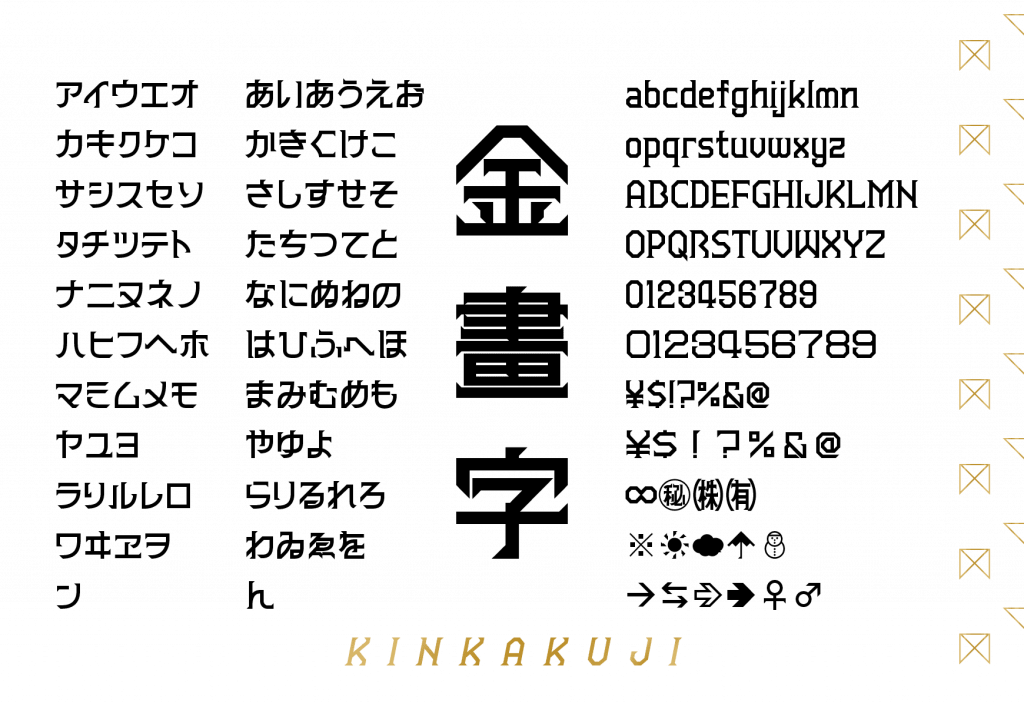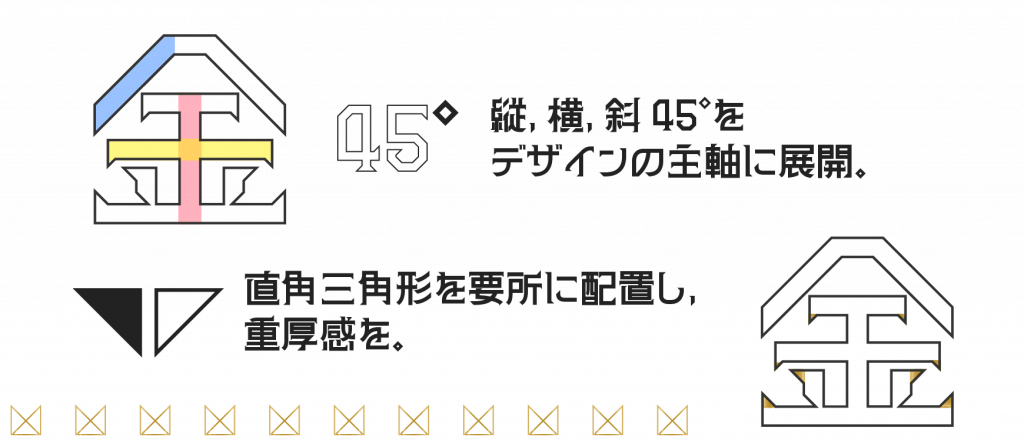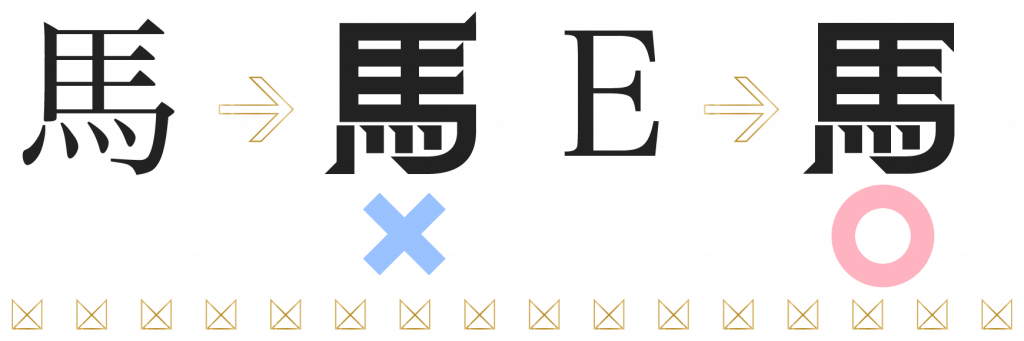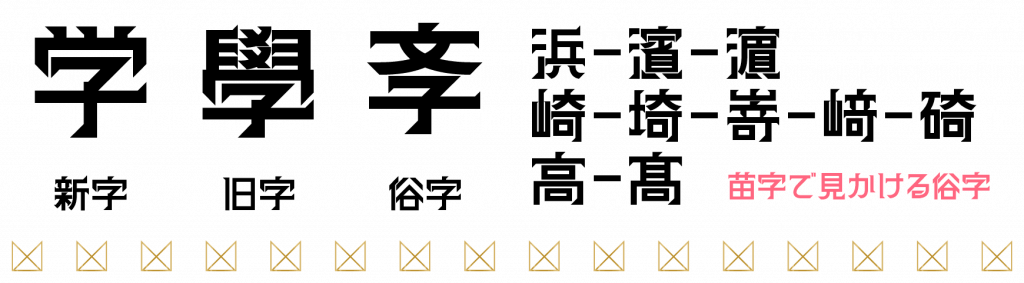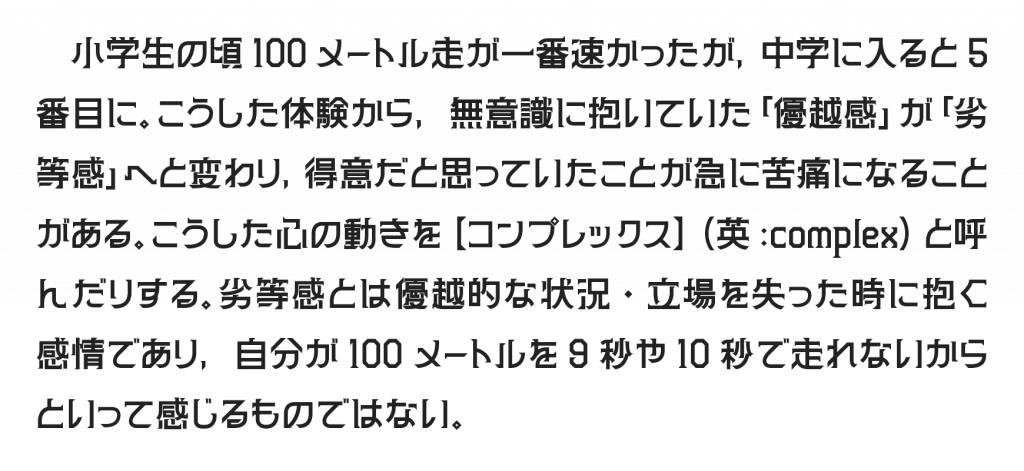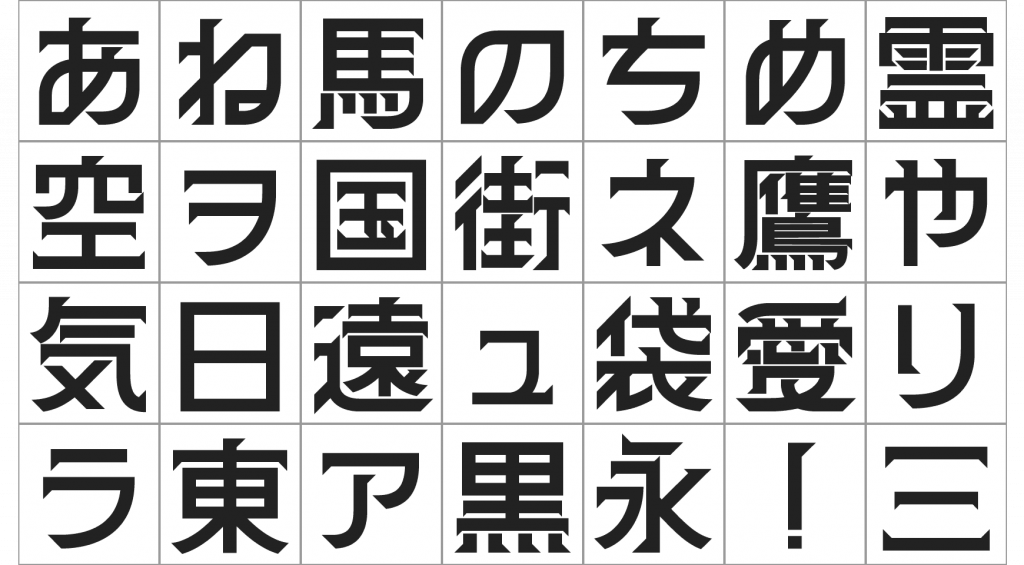
作者从2021年到2022年10月制作的所有字体数据都丢失了,作者要求维修SSD,但被告知交货日期未定且无法恢复,因此放弃了字体的制作工作。
2022 年 11 月,我决定在短时间内创建一个实用的字体,当我看到 Twitter 上流行的“Seido”/ Daisuke Sato 一书的图像时,我想,“这个字符是 45 度吗?”之后开始生产。我们感到欣慰的是,该版本将于 2023 年 2 月完成。
设计以竖、横、斜(45°)直线为主轴展开,排列直角三角形,表达四个角、溅、点、扫。
关于汉字异体字:虽然用得不多,但有JIS一级汉字、旧字、新字,还有很多经常使用的流行字。